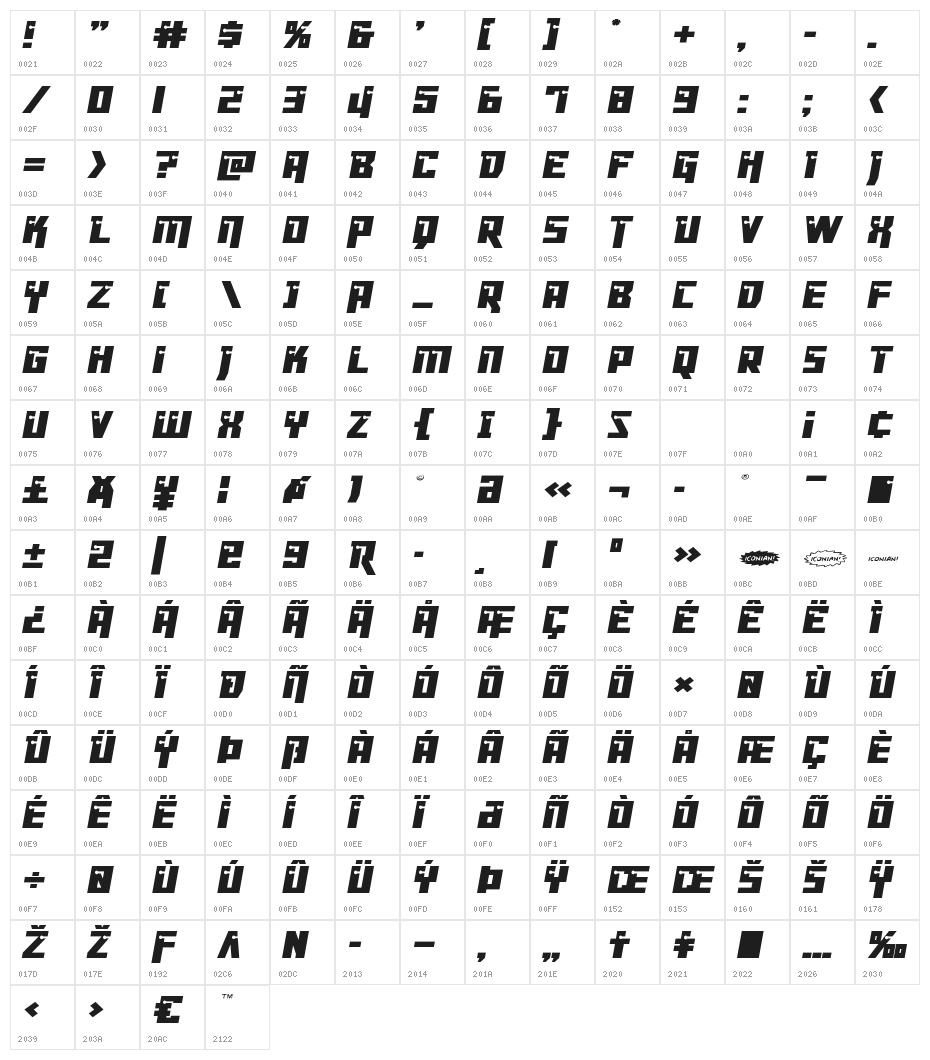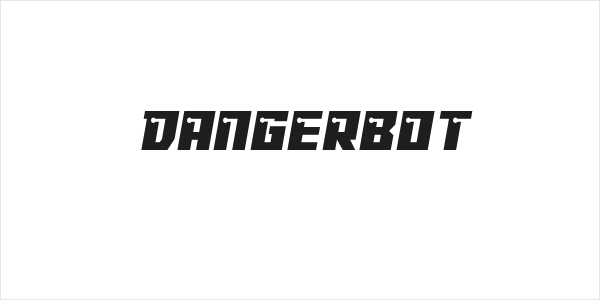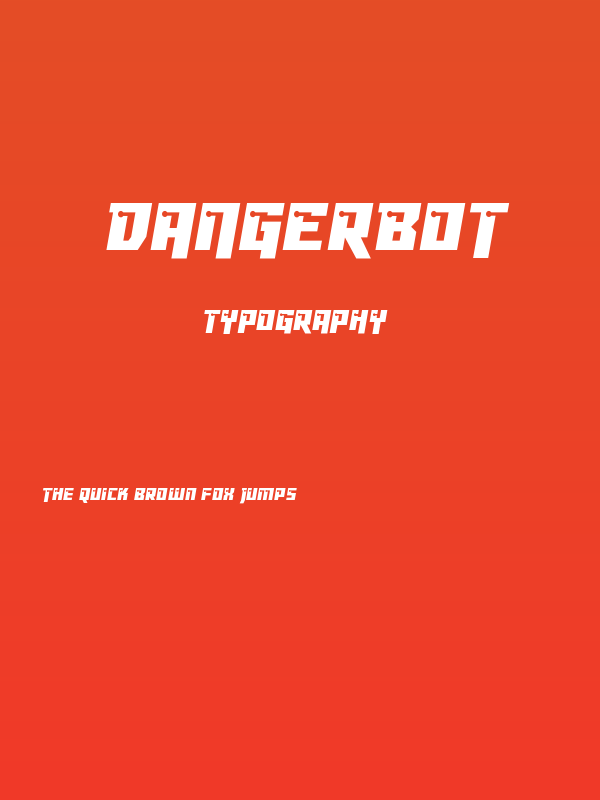
Dangerbot Font
| Stile generale | Futuristic, Modern |
| Progetti proposti | Ideal for video game titles, sci-fi movie posters, tech company branding, and futuristic designs. |